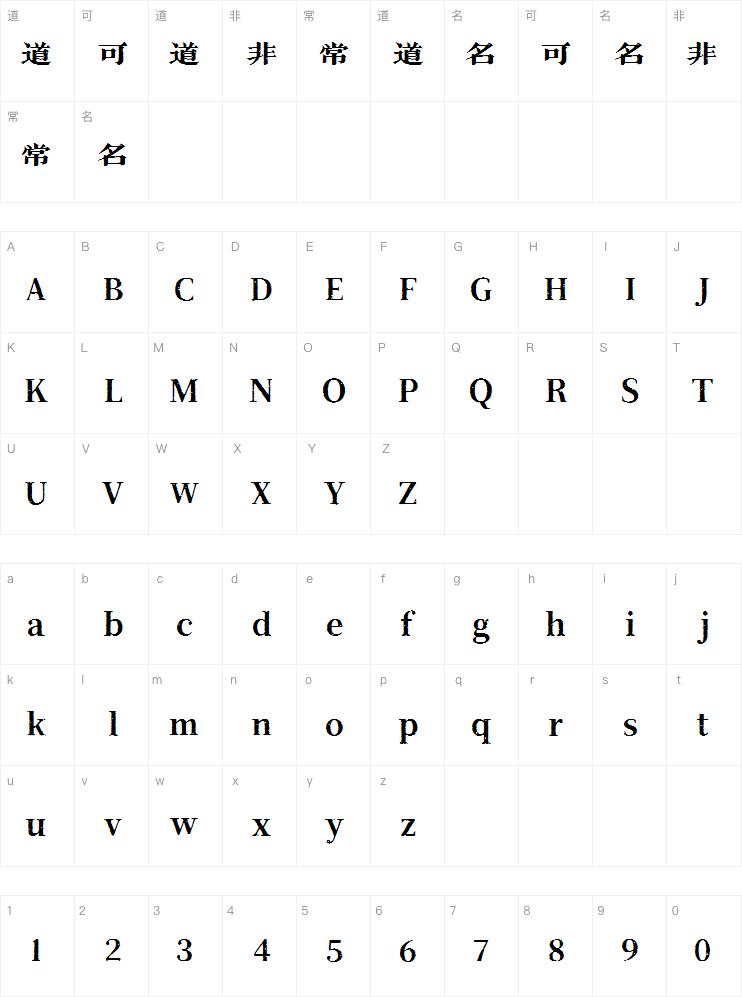
字神武英殿十三经宋简繁-闪 大宋
字神武英殿十三经宋简繁是一款古籍刻本宋体,其从古籍中提取 2000 个核心常用字,还原原初字形结构与笔画特征,并捕捉古籍文字特有的 “时间质感”,保留古籍特有的斑驳感、蚀残痕迹与墨色层次。其复刻不限于对古籍文字的还原,还将字形依照现代简体与繁体字写法扩展至覆盖国标编码,满足不论简繁的日常规范化使用,实现古籍字体从陈列研究到 “可实用、可适配” 的价值转化。适用于书籍装帧、出版印刷、艺术展然、国潮设计、文化宣传等场景。
字神武英殿十三经宋简繁-闪 大宋